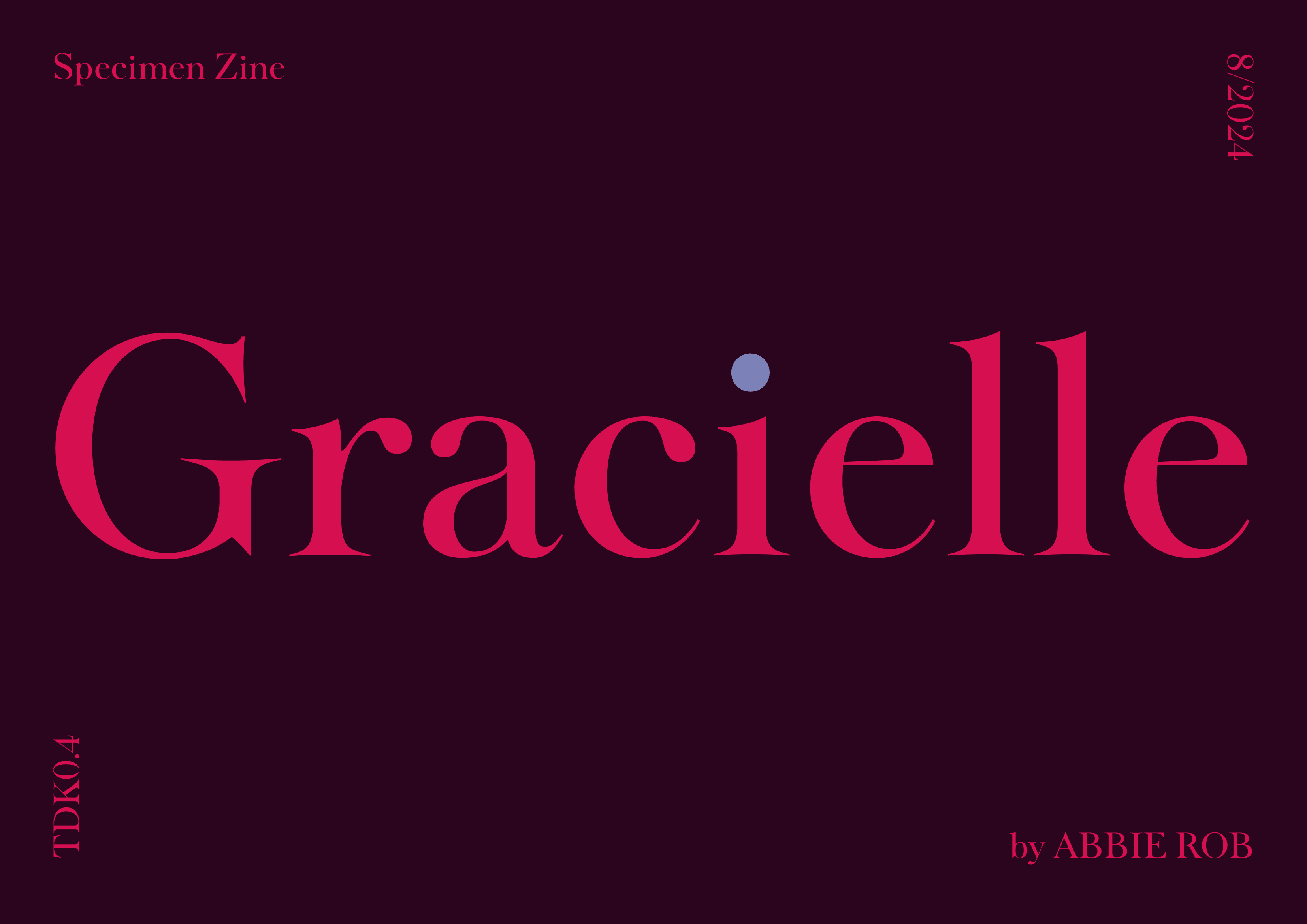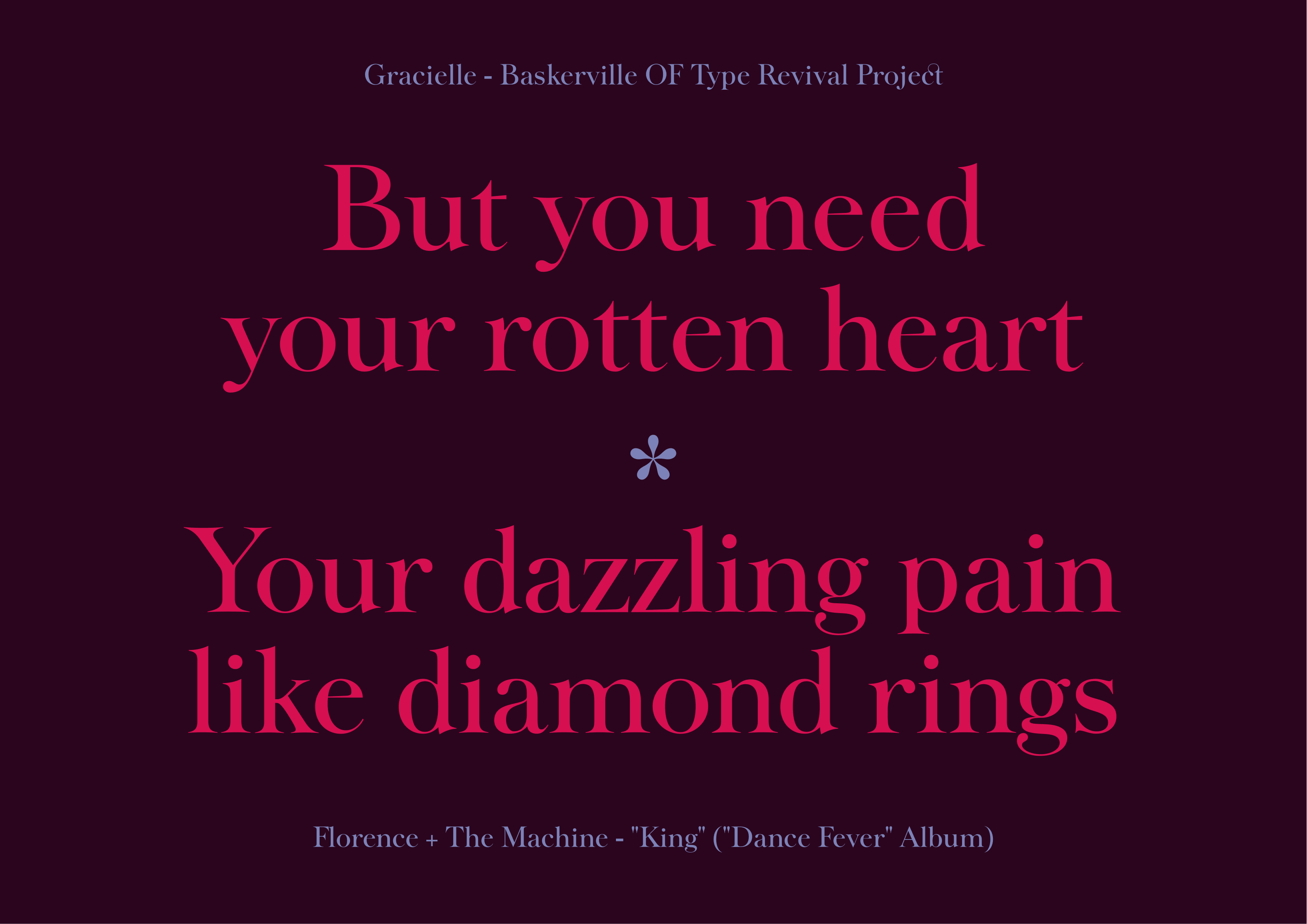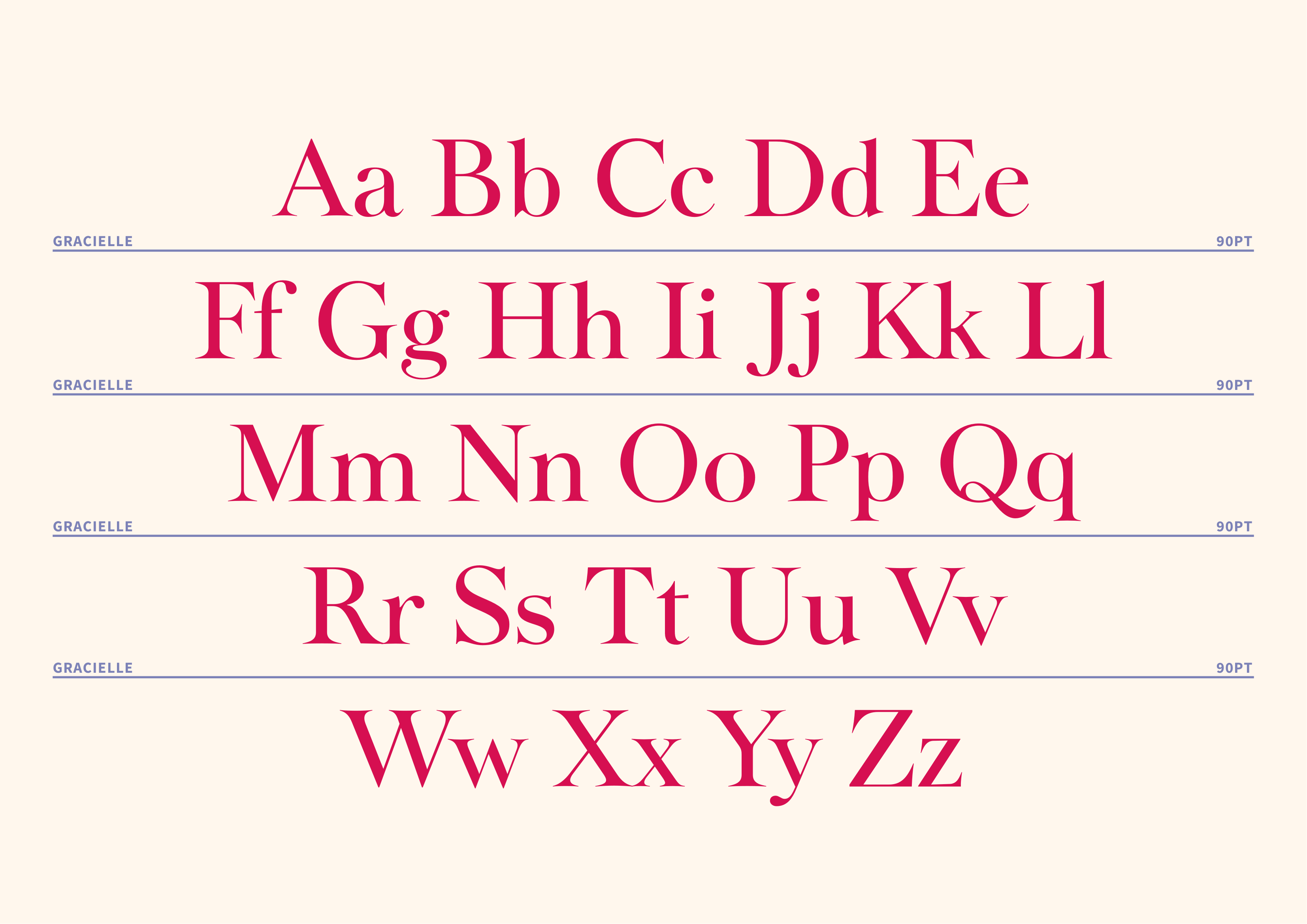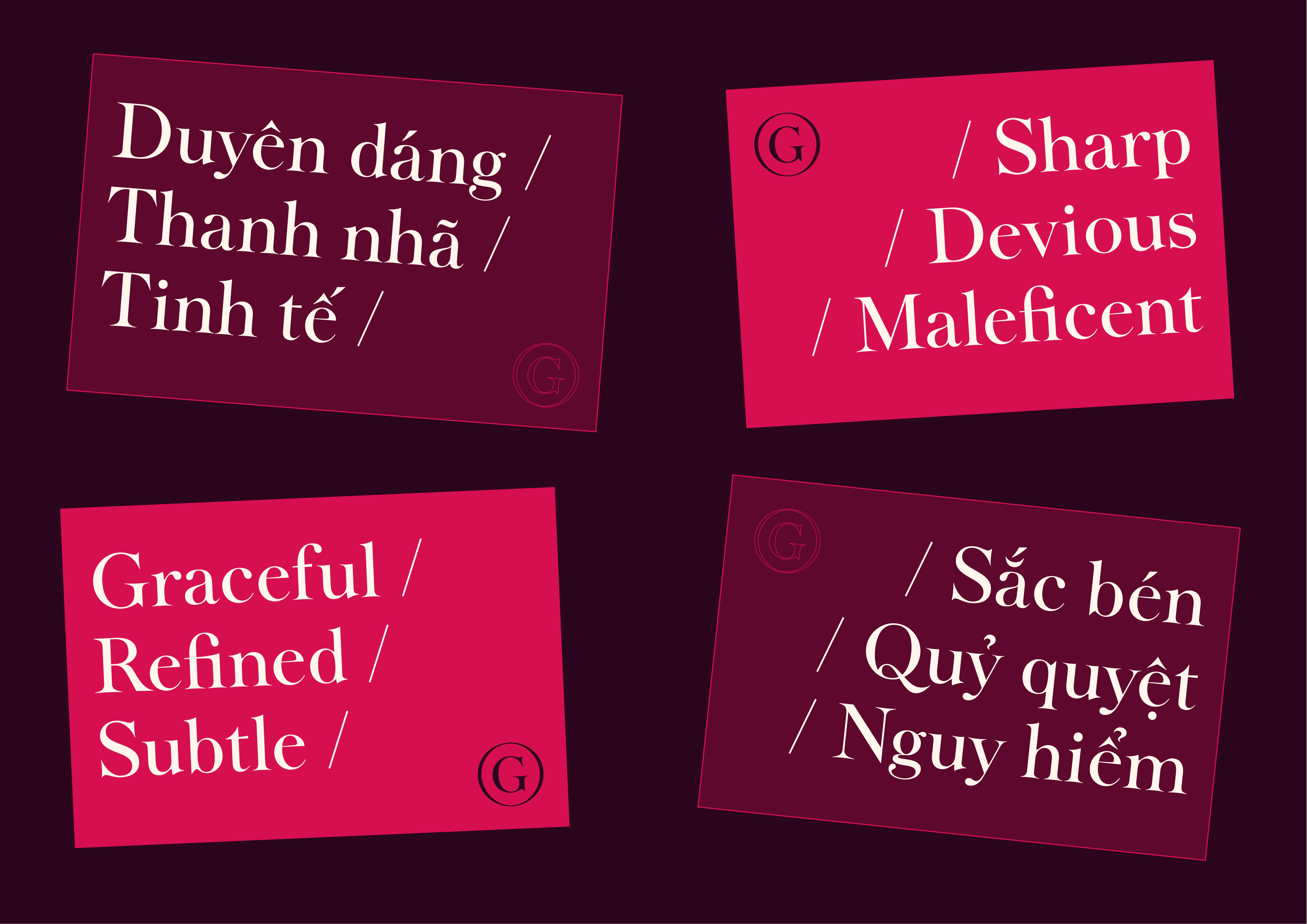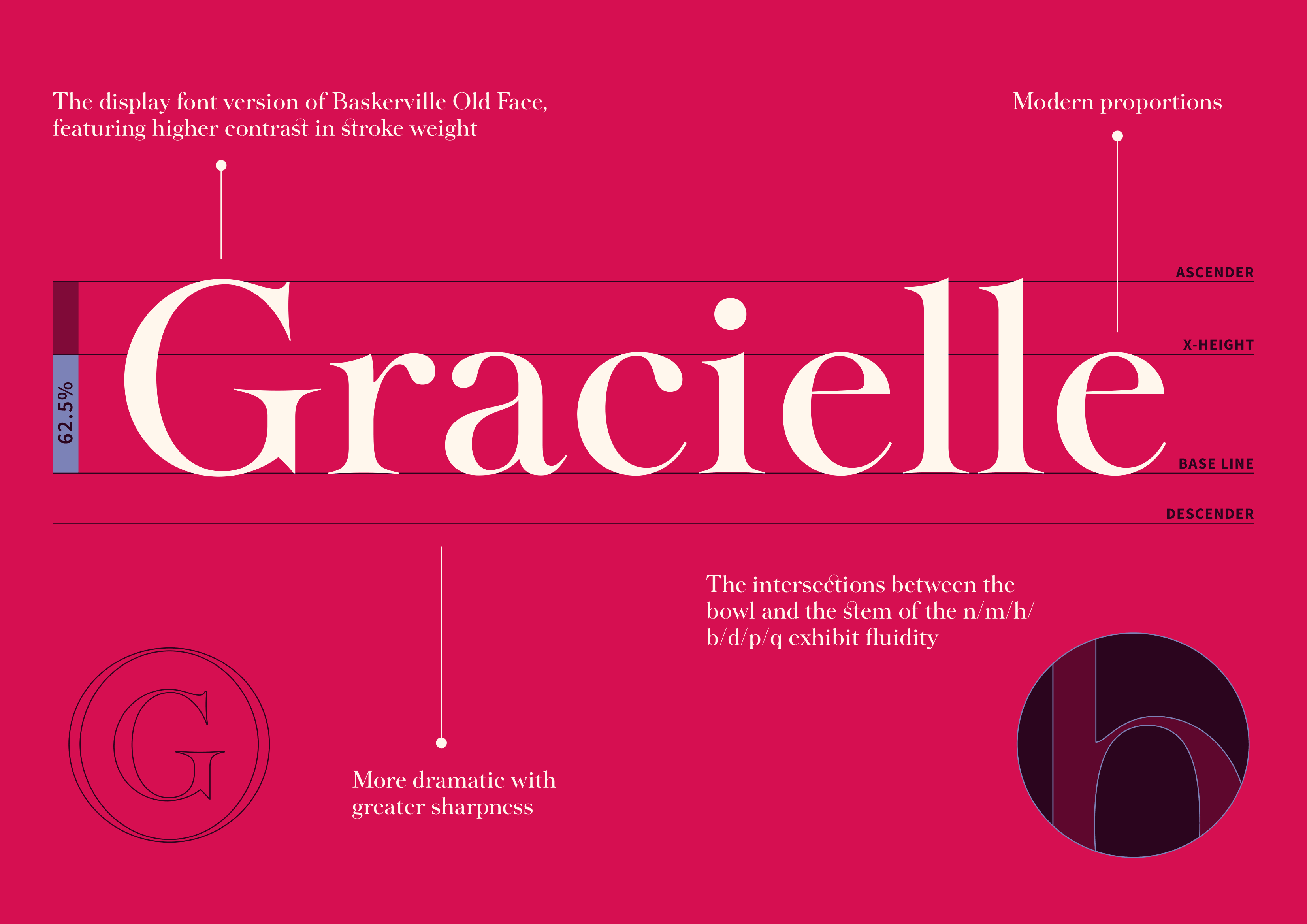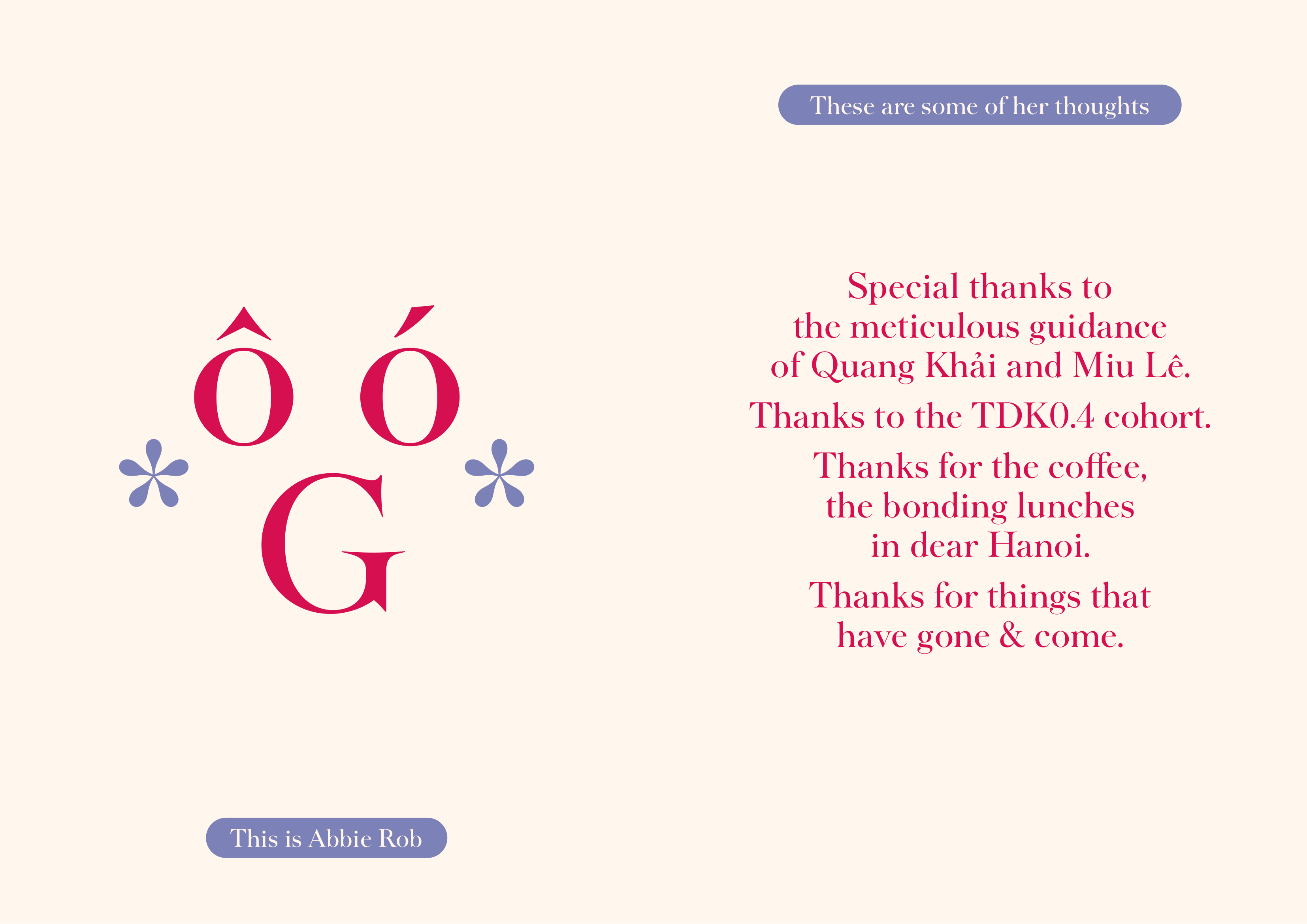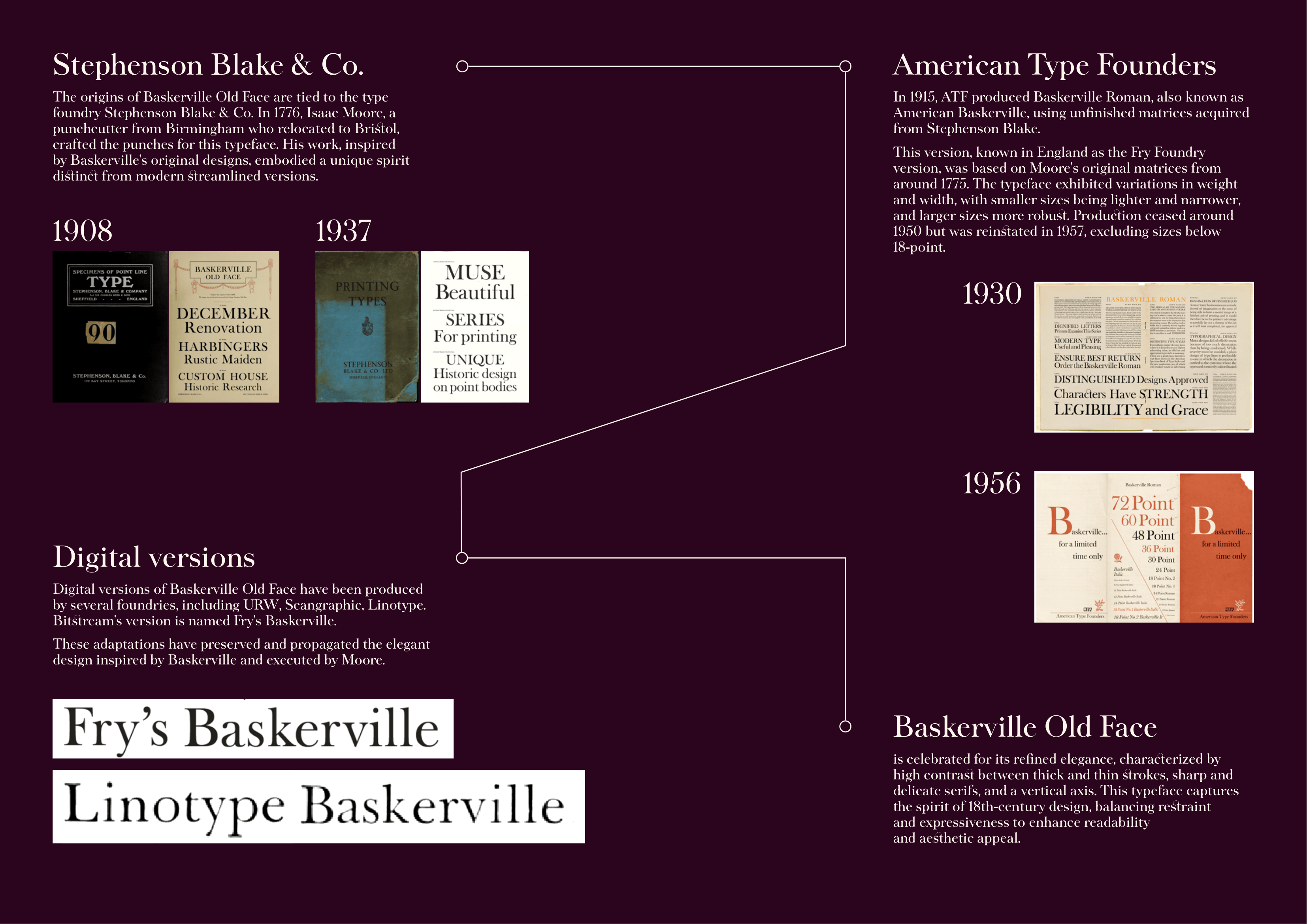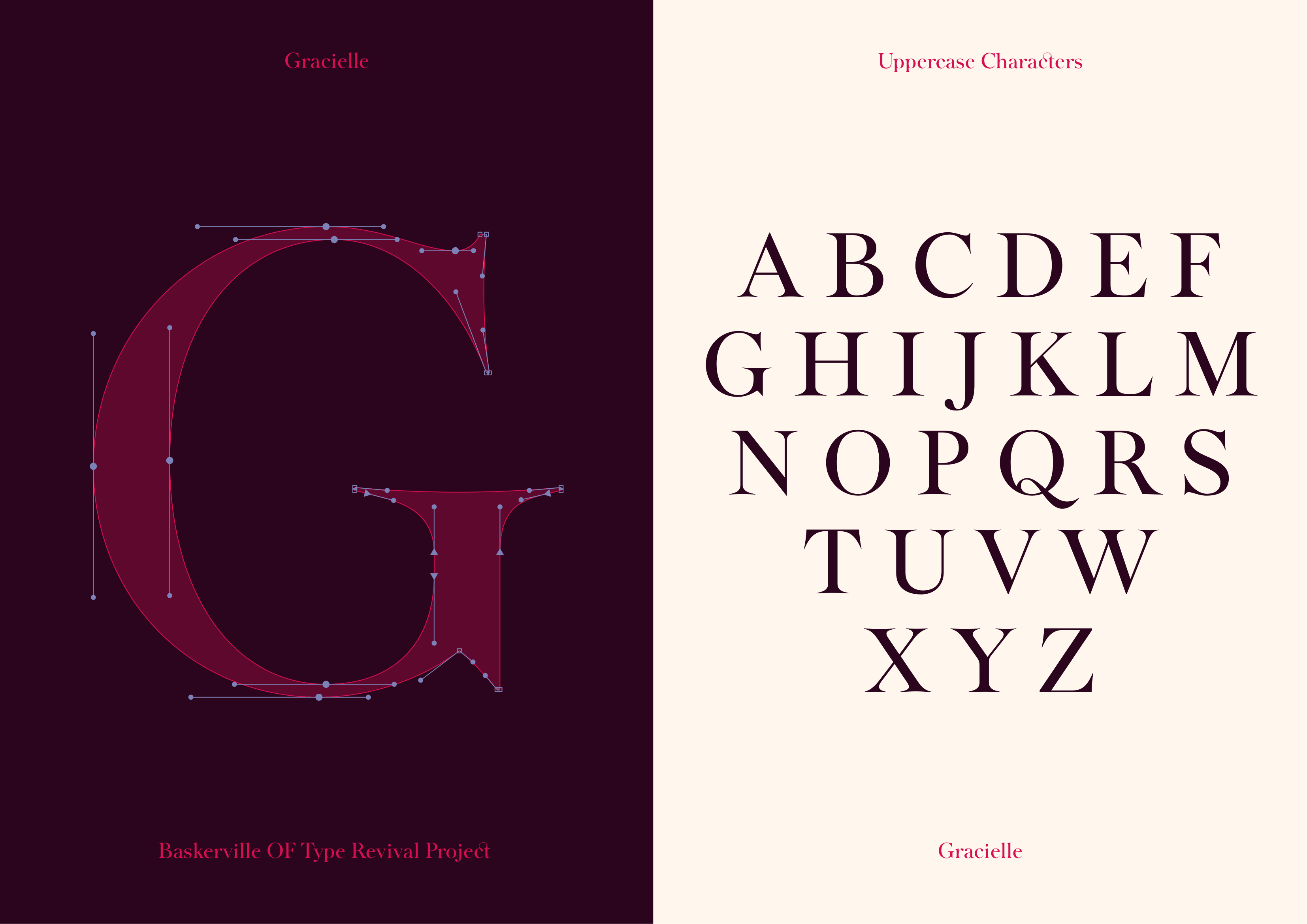
Gracielle
Về Gracielle: Hậu bối của Baskerville Old Face, Gracielle kế thừa mọi điểm đặc trưng nhất từ tỷ lệ thanh đâm rõ ràng tới những vòm tròn căng mọng. Đáy serif hơi vòm nhẹ lên, giọt lệ điệu đà cùng dáng hơi bè đem lại nét duyên dáng, khoan thai cho Gracielle.
Baskerville Old Face is a refined serif typeface rooted in the work of John Baskerville in the mid-18th century, marking a transition between old-style and modern typefaces.
Gracielle
It is characterized by its high contrast between thick and thin strokes, sharply defined serifs, and a more vertical axis compared to earlier humanist designs like Garamond. Baskerville aimed to improve both the clarity and elegance of printed text, using smoother paper and darker ink to enhance legibility and precision. Baskerville Old Face, as a later revival, preserves this balance of readability and sophistication, making it especially suitable for book design, editorial work, and formal printed materials where a sense of tradition and quiet authority is desired.